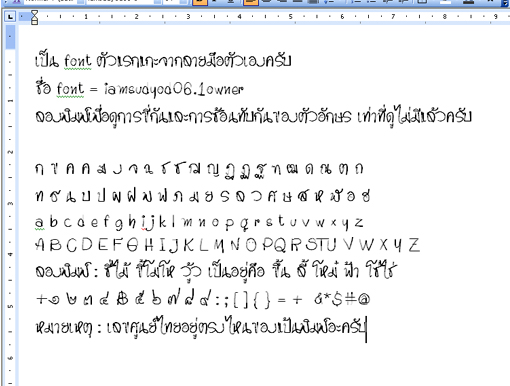
font ตัวแรกลองทำมาให้ดู
ปั่นมา 2 วันอ่านเอาตามกระทู้ในนี้
แกะมาจากลายมือตัวเองทั้งภาษาไทยและอังกฤษ
เห็นชัดขึ้นมั๊ยครับ
สำหรับเลขศุนย์ไทย ผมก็งงเหมือนกันว่ามันอยู่ตรงไหน พี่ๆ ช่วยบอกหน่อยครับ
-- เอาตัวอย่างฟอนต์ใหญ่ๆหน่อยนะ มองยากจัง
ว่าแต่ภาพเล็กไปหน่อยนะ
เลข ๙ ไทย เหมือนเลข ๘ ไทย เลยครับ
และอย่าลืมเลข ๐ ไทยด้วยนะ
ป.ล. เลข ๐ อยู่ตรงตัว Q นะคะ
อย่างนั้น เลข 0 ไทยผมทำแล้วครับ
ช่องไฟแคบจังครับ แต่ไม่แน่นะถ้าดูใหญ่ๆ อาจจะสวยเลยก็ได้  :02:
แก้เสร็จแล้วล่ะครับ